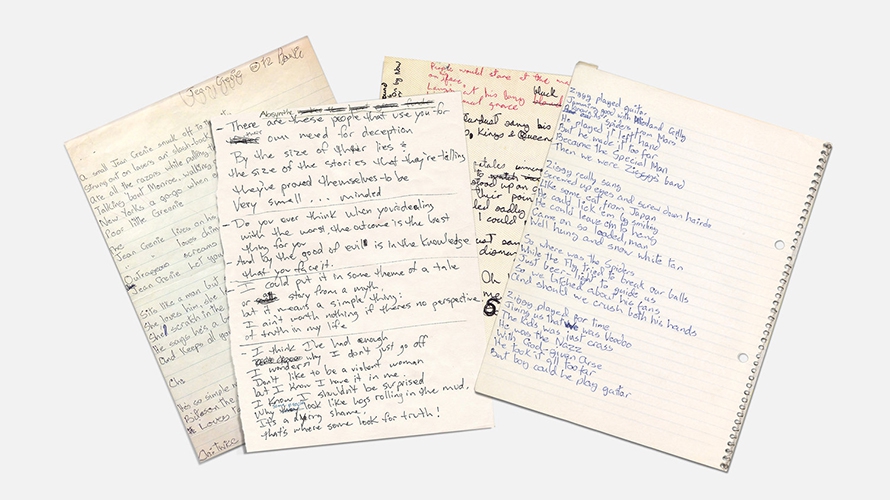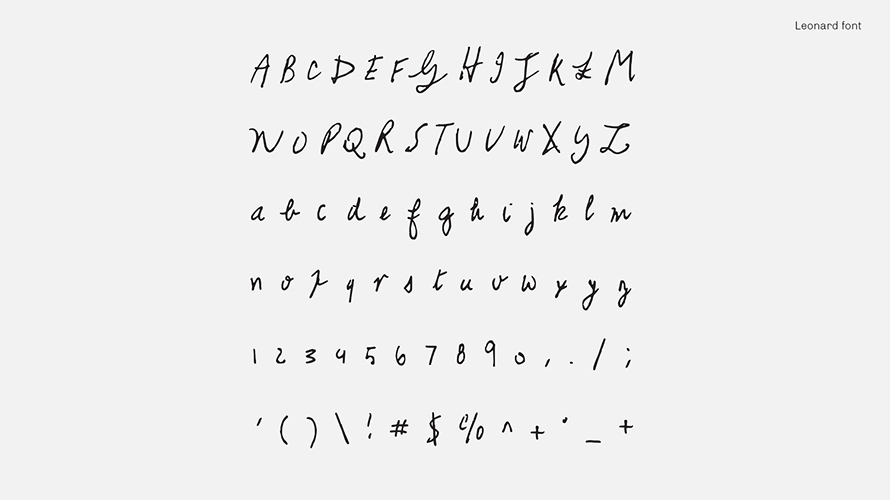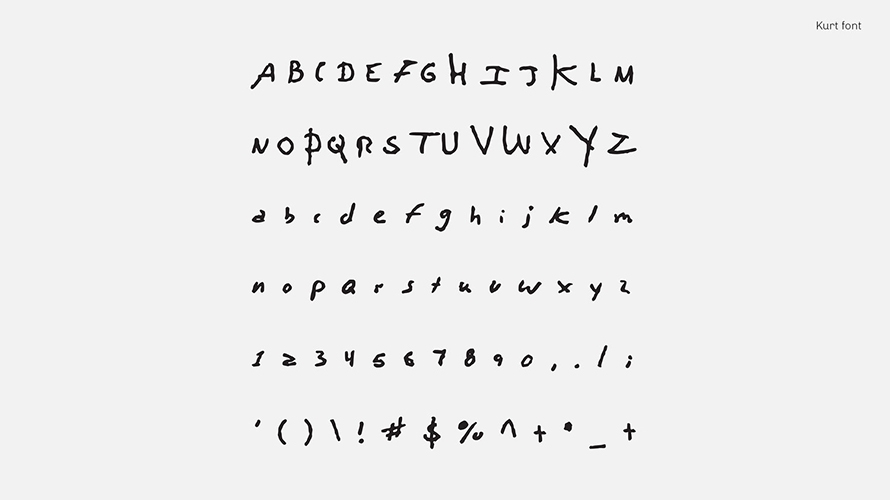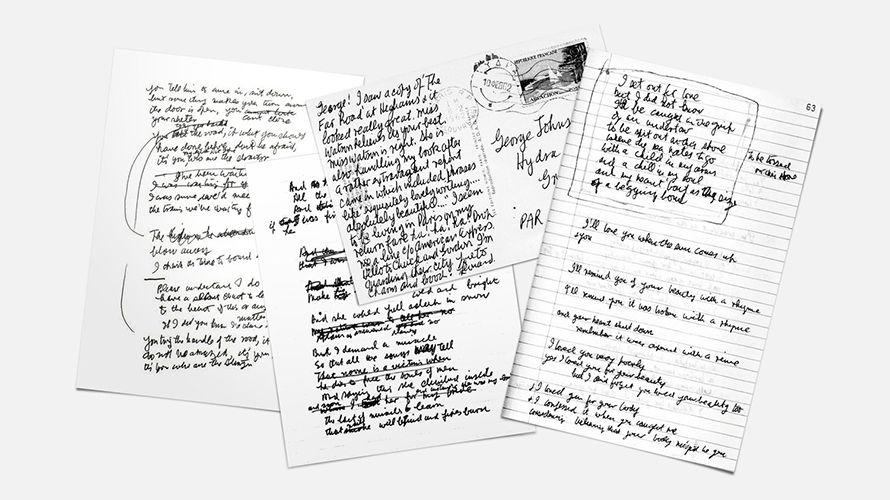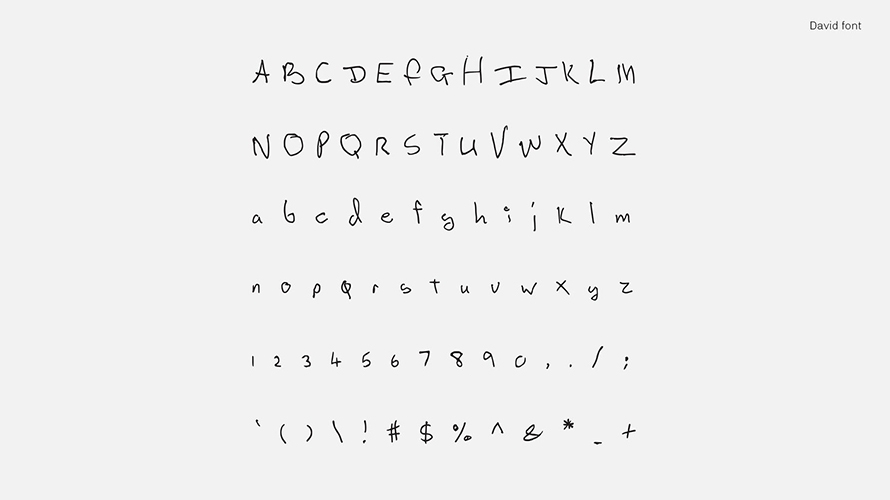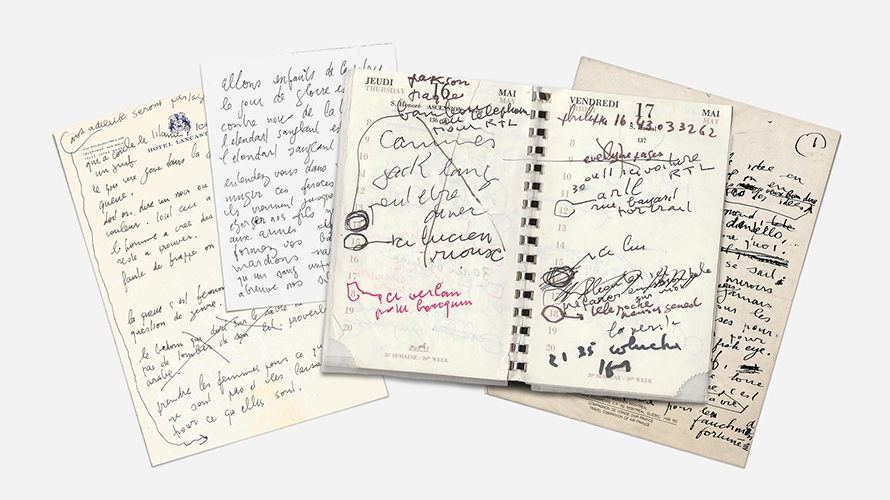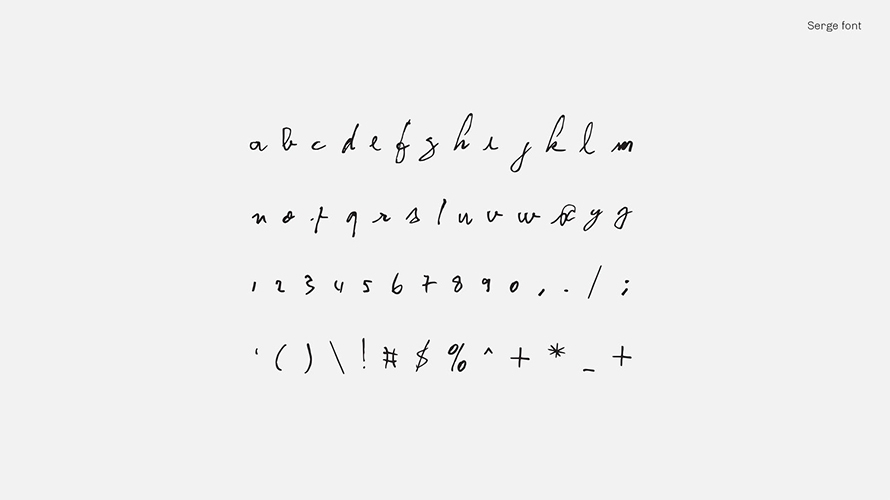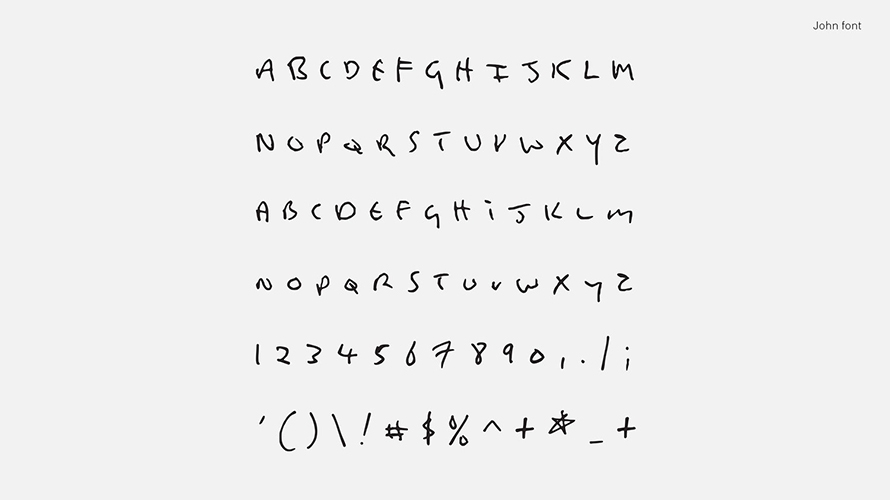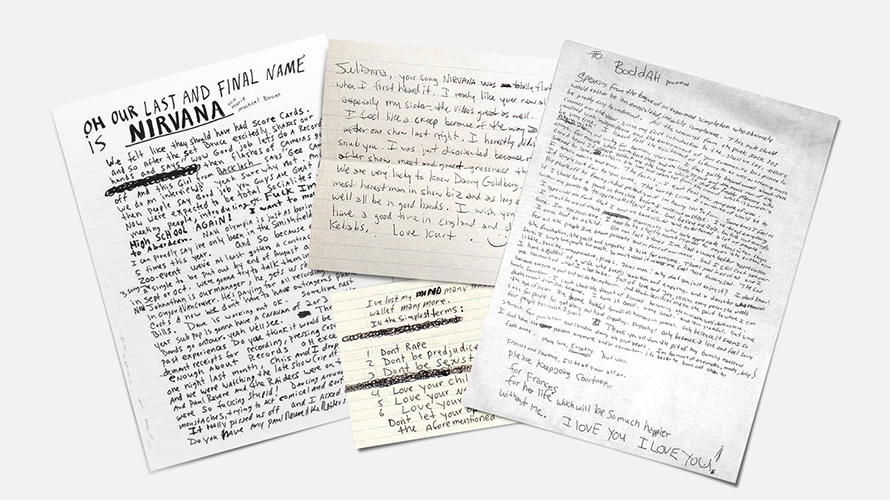
В почерке великих музыкантов всегда есть что-то особенное. Они в порыве вдохновения «на коленке» записывали строчки своих легендарных песен, второпях давали свои автографы толпе поклонников, а некоторые даже писали письма в будущее — так сказать, для потомков.
Французские креативщики Nicolas Damiens и Julien Sens, работающие в JWT New York, реализовали проект по созданию шрифтов на основе почерка своих кумиров.
Почерки пяти музыкантов — Курта Кобейна, Дэвида Боуи, Джона Леннона, Леонарда Коэна и Сержа Гейнсбурга — стали шрифтами для «личного употребления» (без возможности коммерческого использования, например, брендами).
Однако после новости на Adweek сайт проекта, на котором можно было скачать шрифты легендарных музыкантов, был заблокирован его создателями под давлением неких неуполномоченных владельцев авторских прав на наследие музыкантов.
Вместо шрифтов на сайте появился прощальный пост, в котором авторы проекта признаются, что их главным намерением было — вдохновить музыкантов на дальнейшее творчество, ощутить присутствие рядом музыкальных легенд, однако из-за юридических аспектов дела инициативу необходимо закрыть.